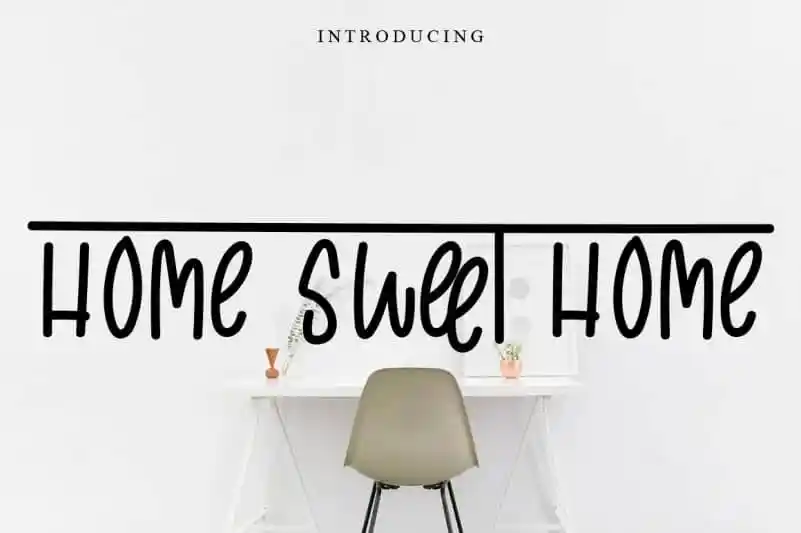
Home Sweet Home Handwritten Font – Download Grátis
A fonte ‘Home Sweet Home Handwritten Font’ é uma escolha perfeita para aqueles que buscam personalidade e simplicidade na sua tipografia. Desenvolvida pelo designer LevinCreative, essa fonte é delicada e descontraída, com traços finos que remetem a escrita de um amigo leal ou colega de trabalho amigável. Com suas letras quase naturais e aconchegantes, esta font irá adicionar uma camada única à sua identidade visual, independente do tema ao qual seja aplicada – seja em logotipos, materiais promocionais ou até mesmo em conteúdo digital como blogs e sites pessoais. Esta font é uma ótima opção para aqueles que buscam um touch personalizado sem perder a essência de uma marca. Com ‘Home Sweet Home Handwritten Font’, você pode tornar qualquer projeto mais acolhedor e único, transformando simplesmente textos em arte.